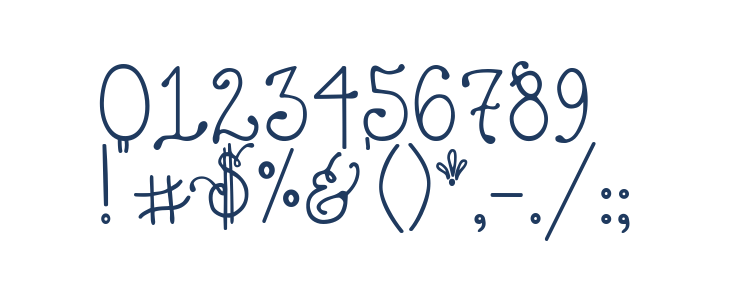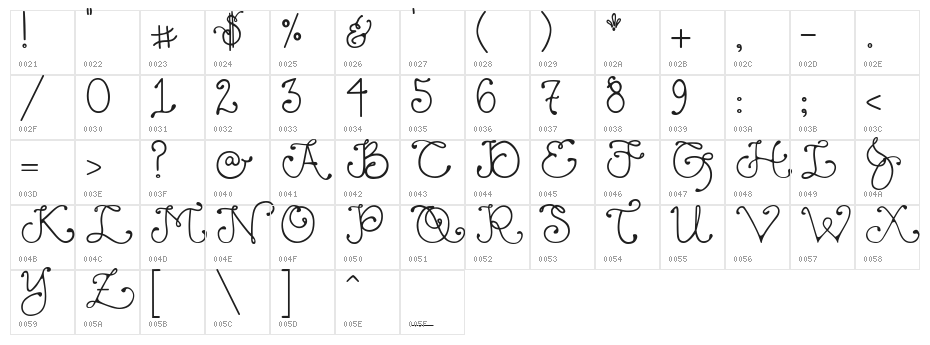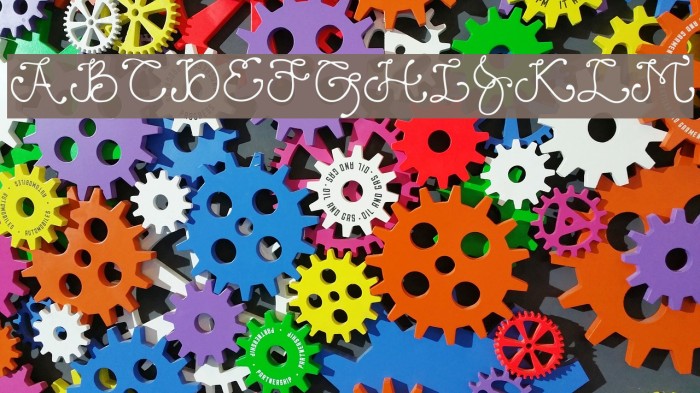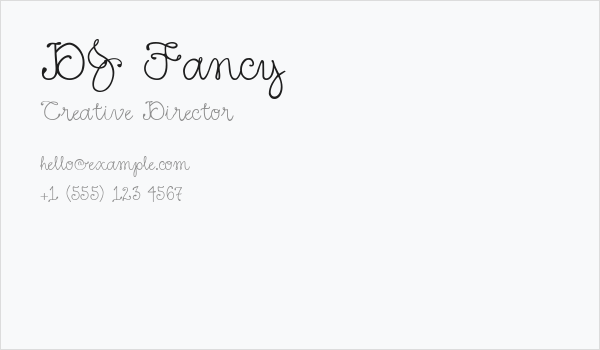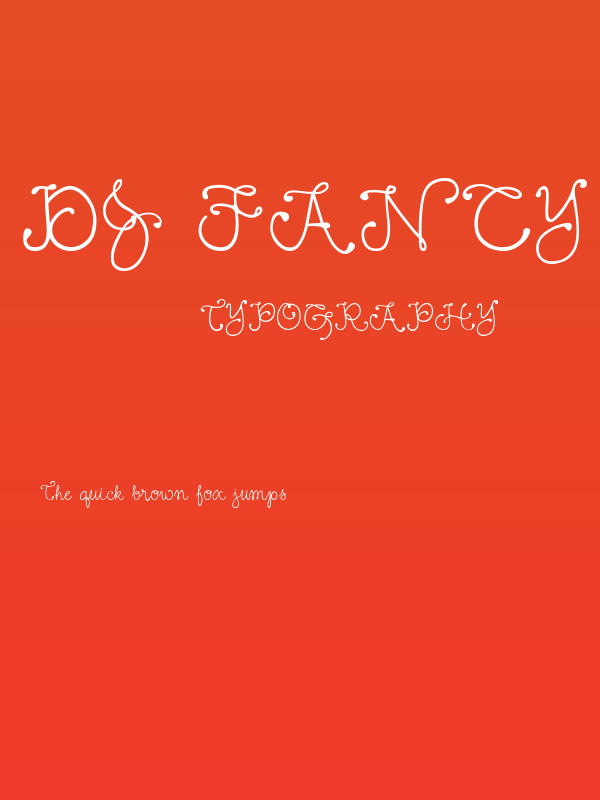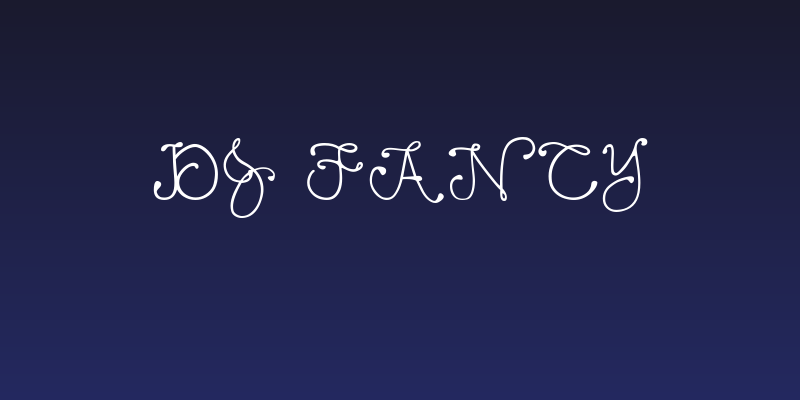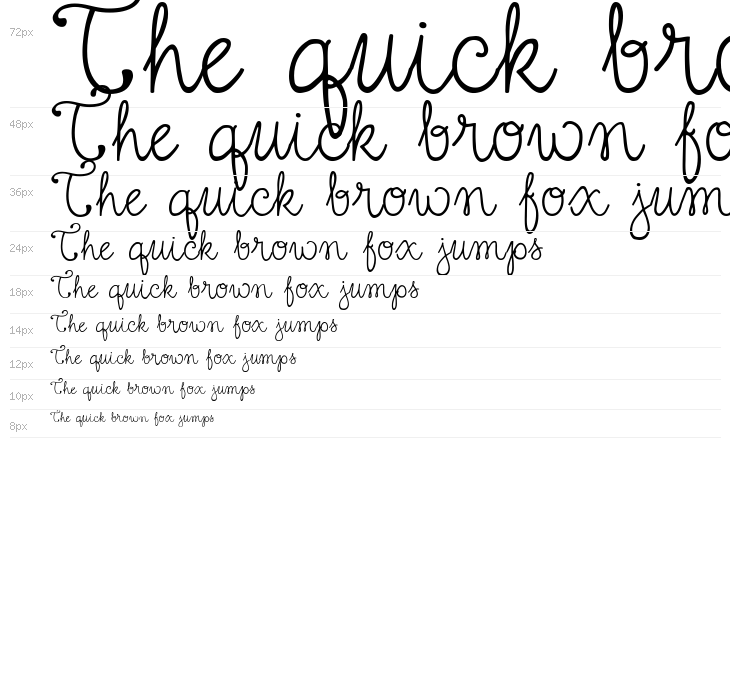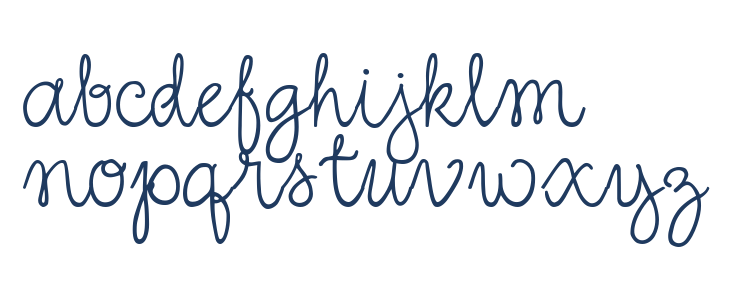
DJ Fancy Font
| 用途 | Logos, Invitations, Artistic Posters |
| おすすめプロジェクト | Ideal for invitations, greeting cards, playful branding, and artistic posters. |